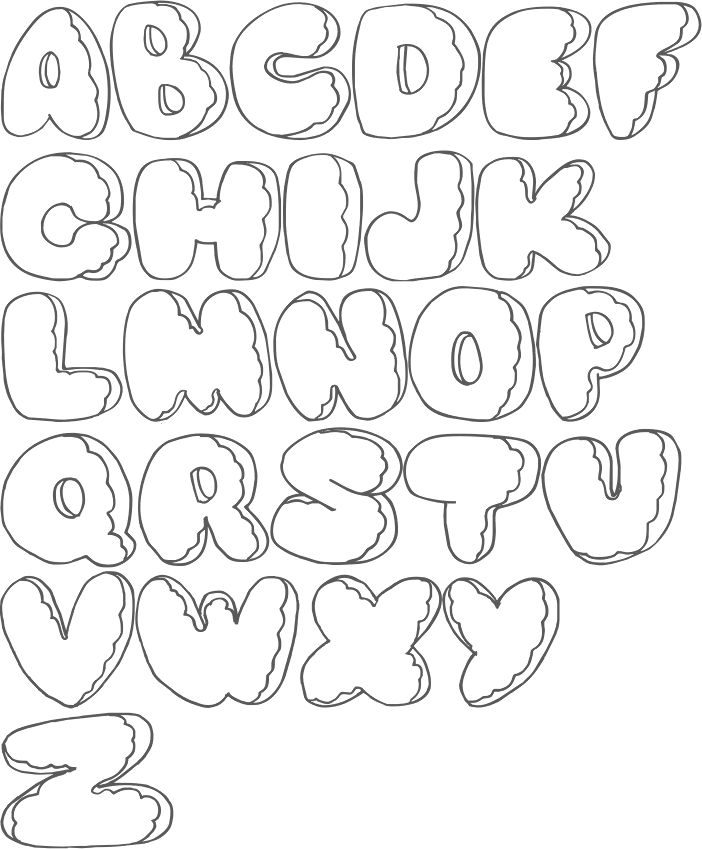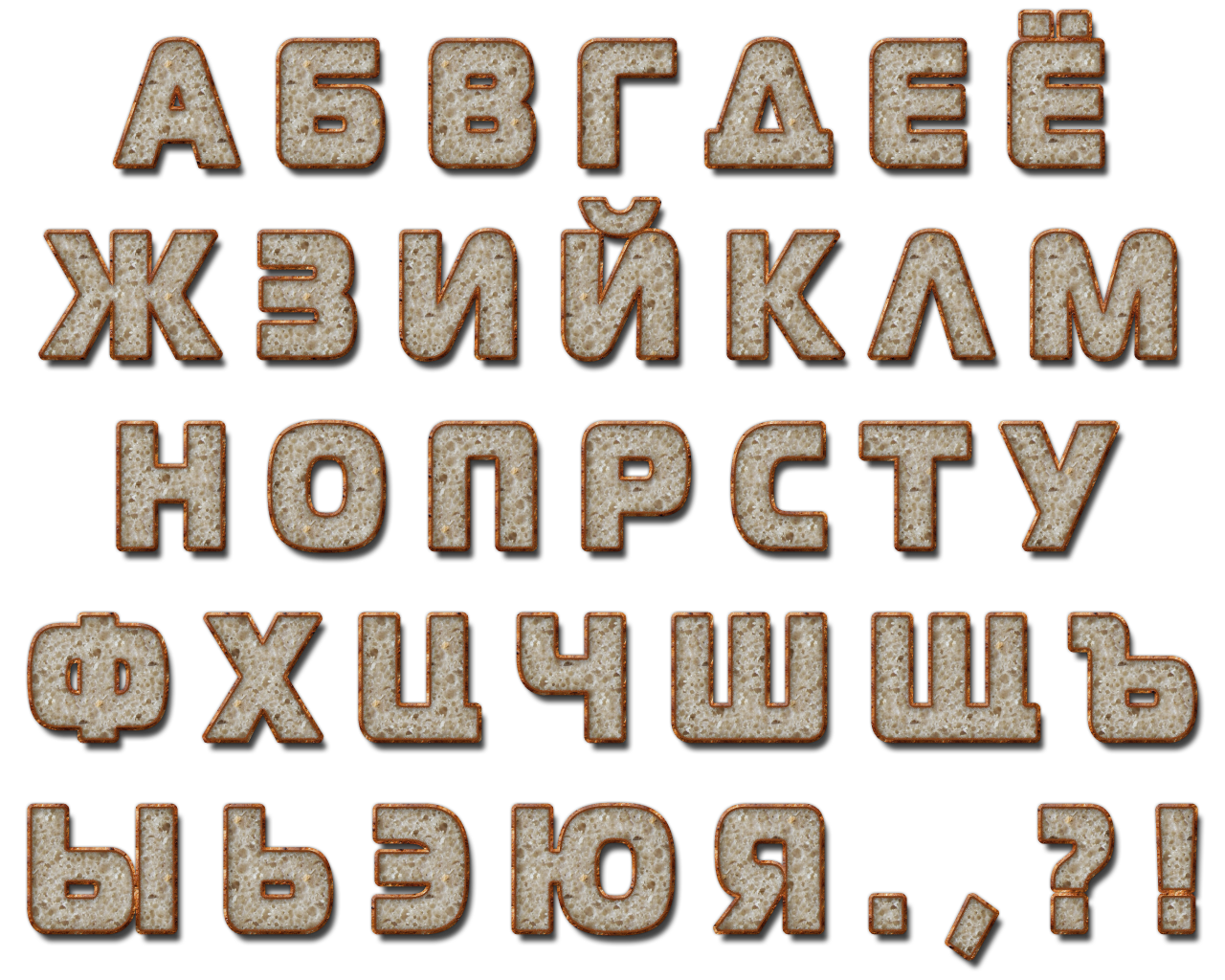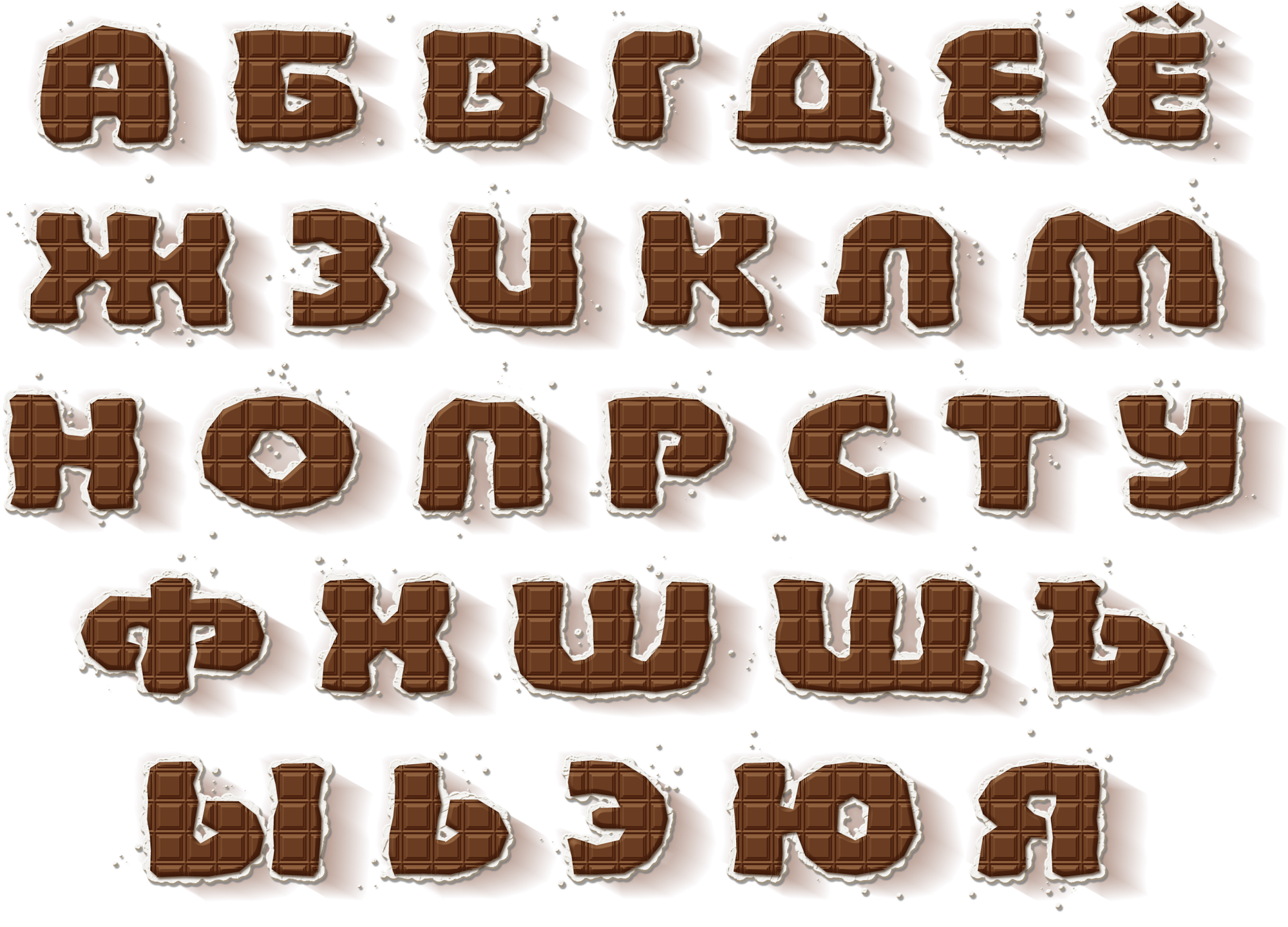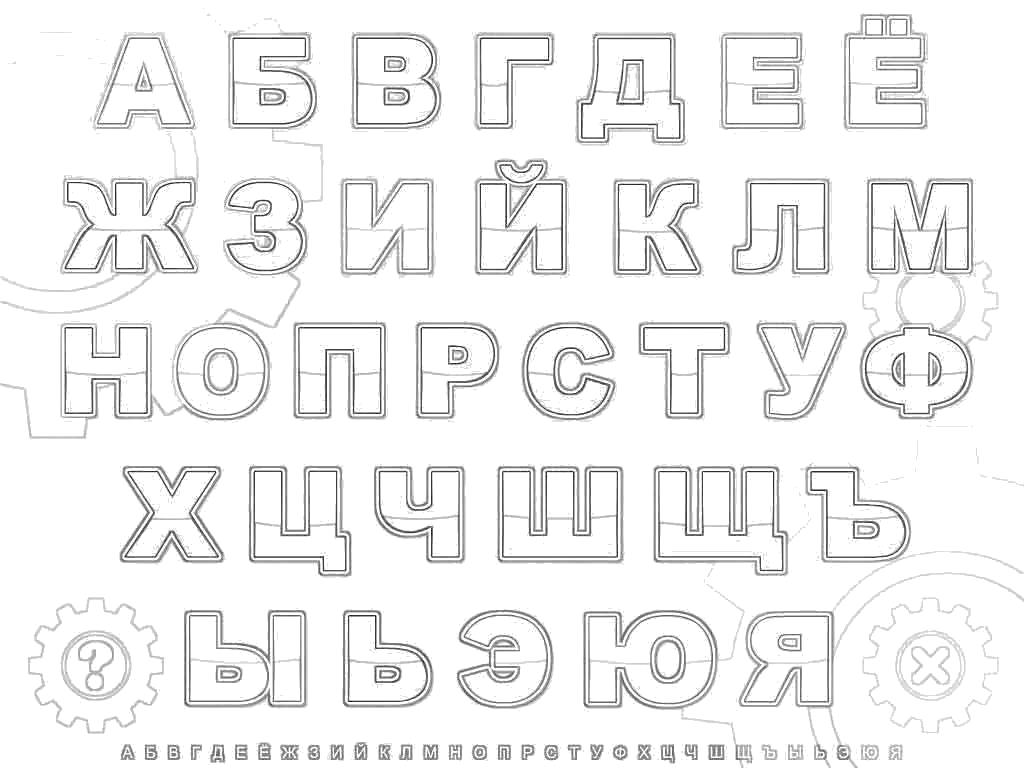
Объемные русские буквы для рекламы на зданиях Москвы
Графологи и психологи утверждают, что глаз человека одновременно охватывает форму и длину строки. Простые геометрические формы воспринимаются быстрее, чем сложные, неправильной формы. Поэтому с помощью правильного подбора шрифтов, размеров оказывается о психологическое и эмоциональное воздействие на человека. Уже в начале 20 века наглядно-изобразительные возможности шрифтов русского алфавита использовались в рекламных целях, украшали городскую среду, участвовали в создании имиджа и продвижения компании.
Как используются
Главное назначение конструкций из объемных знаков — реклама на фасадах, стенах и крышах зданий. Правильно оформленная вывеска выполняет сразу три функции: декоративную, информационную и рекламную. Объекты, на которые устанавливается надписи из объемных букв — это торговые центры, гостиницы, различные офисные и административные здания.
Ярко оформленные названия, логотипы, указатели запоминаются и привлекают внимание потенциальных клиентов. Наружные рекламные конструкции в вечернее время подсвечиваются. Объемные буквы с подсветкой устанавливаются на любой высоте — надпись хорошо видна издалека в темное время суток. Светящаяся реклама всегда привлекает взгляды прохожих яркостью и презентабельностью.
Буквы русского алфавита применяются не только в наружной рекламе для создания вывесок — их с успехом используют и для внутреннего убранства помещений. Они отличаются формами, размерами, цветом, имеют витиеватый или простой шрифт. Дизайн интерьера с объемными элементами смотрится стильно и оригинально. Этот способ декоративного оформления используется в следующих случаях:
- Декорирования банкетов и торжеств в ресторанах или кафе
- Оформления стендов на выставках
- Украшения стен в детских садах, школах и офисах.
- Жилые комнаты, украшенные объемными надписями, приобретают индивидуальный стиль.
- Красочный цветной алфавит, используемый для оформления детской комнаты, станет элементом декора послужит развитию ассоциативного мышления.
Как выбрать
Для рекламных целей используются наглядно-изобразительные различия в курсивном и печатном начертании. Курсивное начертание отличается характерным наклоном справа налево и сверху вниз, и зрительно напоминает рукописный почерк. Читаемость курсива уступает удобочитаемости прямому начертанию, но эффектность и притягательность для взгляда выше. Возникают такие ситуации, когда человек не имеет четко сформированной позиции по выбору того или иного стиля русского алфавита. Чтобы найти оптимальный вариант, нужно вместе с нашими специалистами рассмотреть макеты конструкций из объемных букв с различным сочетанием шрифтов, начертания и цвета букв.
Рассмотрим различные варианты изобразительных возможностей шрифтов русского алфавита:
- Применение декоративных древнерусских стилей написания для современных вывесок
- Современные стили написания, большинство которых встроены в компьютерный софт – Arial, Times New Roman
Приведенные примеры вывесок носят информативный характер, но в каждой вывеске просматривается тенденция создания лица компании. С помощью применения различных технических средств и выбора шрифта удается придать вывескам уникальность, повысить узнаваемость бизнеса.
Русский алфавит в граффити. Семь кириллических шрифтов граффити
Многие райтеры имеют свой стиль и придумывают самостоятельно . Но все равно существуют основные принципы и шрифты, которыми пользуется большинство.
Я тоже иногда придумываю свои буквы и зарисовываю их на бумаге, во-первых, чтобы не забыть, а во вторых, воспроизводить на стене знакомый шрифт потом легче, чем изобретать что-то на ходу.
Самые распространенные стили написания и буквы граффити
Баббл
Такие мультяшные объемные буквы – самый распространенный вариант. В шрифте баббл буквы должны сливаться и как бы наплывать друг на друга. Единственный минус – иногда прочитать, что написано в этом стиле довольно трудно, так как буквы могут искажаться практически до неузнаваемости.